Schriftausstellung
Schrift 18.–21. Jahrhundert
Aufklärung, Industrialisierung, Schulpflicht, Computer — kein anderes Zeitalter hat das Schreiben so stark verändert. Vom Federkiel zur Tastatur ist es nur ein gutes Jahrhundert.
Im 18. und 19. Jahrhundert wird Schrift zur Bürgerpflicht: Volksschulen üben deutsche Kurrent, Sonntagsschulen lehren Bibellesen, Kontore verlangen saubere Geschäftsschrift. Stahlfeder und Tinte verdrängen die Gänsefeder, später folgen Schreibmaschine und Kugelschreiber.
Im 20. Jahrhundert lässt das Dritte Reich die Fraktur fallen, die lateinische Ausgangsschrift wird Standard. Mit Computer, E-Mail und Smartphone verschiebt sich das Schreiben endgültig auf Tastaturen und Touchscreens — und die Handschrift wird zu etwas Besonderem.
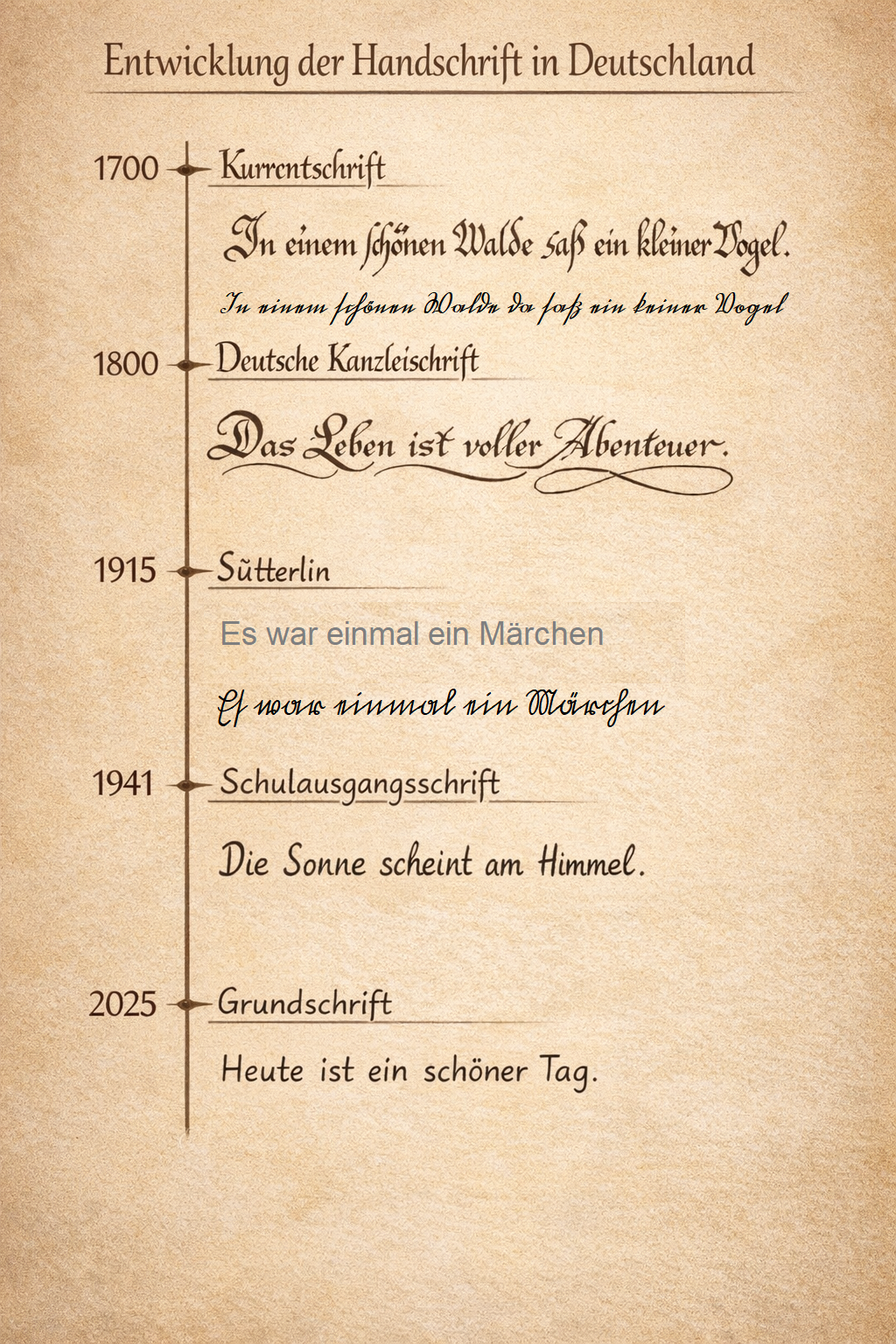
18.–21. Jahrhundert
Von der Feder zur Tastatur
Tafel deutscher Schriftformen vom 18. bis 21. Jahrhundert
Schrift-Tafel
Drei Jahrhunderte im Vergleich
Antiqua und Fraktur, Kurrent und Sütterlin, Schulausgangsschrift und vereinfachte Ausgangsschrift: die Tafel zeigt, wie viele Hände an einem einzigen Wort wie „Deutschland“ über die Jahrzehnte geschrieben haben — und wie sehr sich die Vorstellung von Lesbarkeit gewandelt hat.